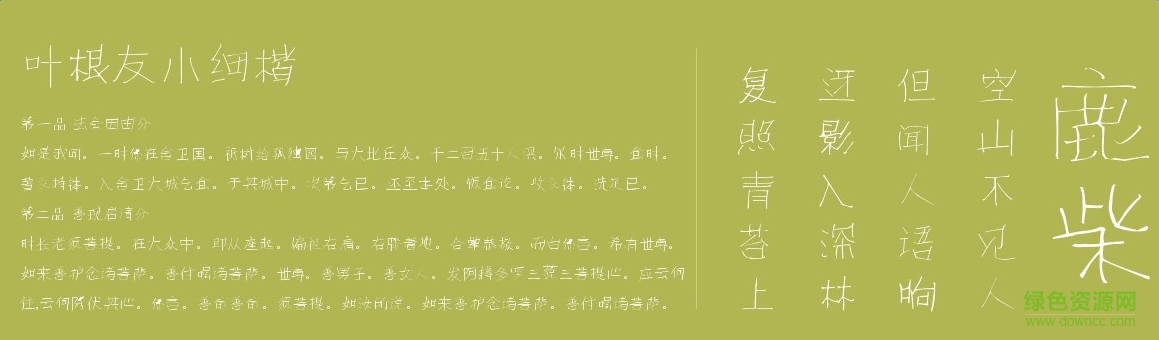
葉根友小細(xì)楷
葉根友小細(xì)楷字體是由中國(guó)書(shū)法奇人,五筆同書(shū)世界首創(chuàng)者,連筆空心字吉尼斯世界紀(jì)錄保持者葉根友先生親自書(shū)寫(xiě)的一款字體,是葉根友先生平時(shí)書(shū)寫(xiě)最多的一種,也是最為實(shí)用的風(fēng)格。字體大方,流暢。歡迎下載!